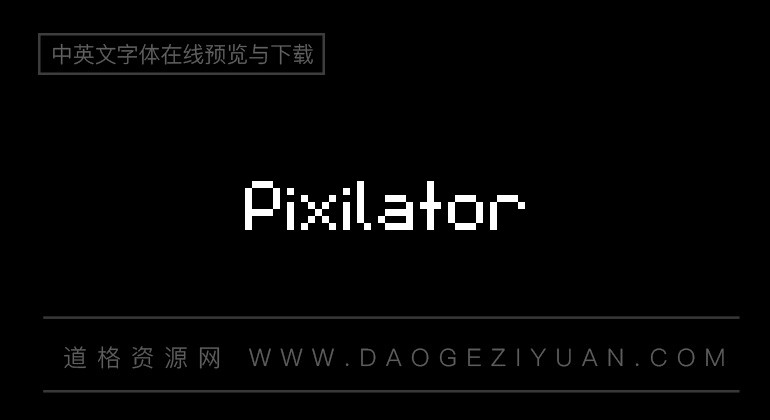
Pixilator字体是一种像素化的字体,它的每个字符都由小的方块组成,类似于早期8位游戏机和电脑中使用的图形。这种字体呈现出一种独特的复古感,可以用于各种不同的设计中,例如游戏、动画、网站设计等等。Pixilator字体通常具有较大的字体大小和强烈的颜色对比度,使其非常适合在小尺寸屏幕上使用。此外,由于其简单的设计,Pixilator字体在数字艺术、流行文化和设计爱好者之间非常流行。文件名:Pixilator-1.ttf